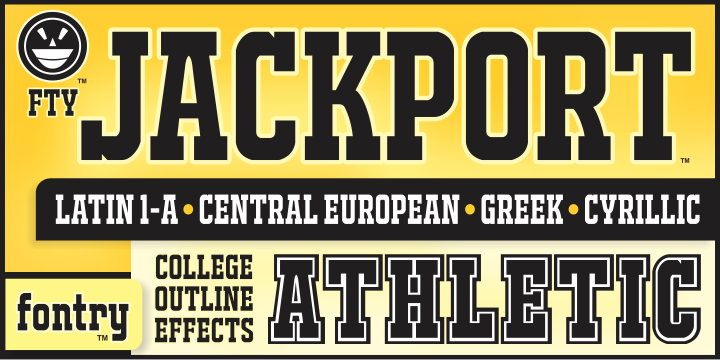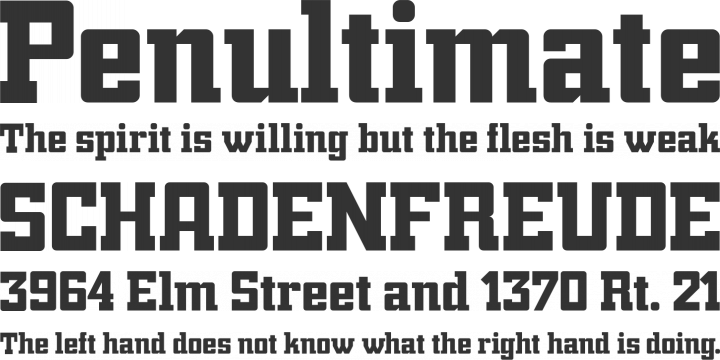
Suche schmale aber hohe Schrift ähnlich College
suche eine hohe Schriftart, die aber auch schmal sein soll.
Außerdem soll sie der College ähneln bzw. zum Thema Abschluss passen.
Wäre auch sehr gut wenn diese Umlaute hat.
Dieser College hier? Die ist ja für die Richtung schon relativ schmal, eine weitere Auswahl wäre hier, z.B. die Octin-Varianten (nur Majuskeln, Umlaute vorhanden, aber kein großes sz).
mir fallen da zwei relativ schmal laufende Schriften ein. Beide laufen schmaler als die Octin Sports.
Jackport NCV, nur Großbuchstaben, frei für nichtkommerzielle Nutzung,
Porn Star Academy *rotwerd* nur Großbuchstaben, keine Unlaute und scharfes s, frei für nichtkommerzielle Nutzung,
Hier noch zwei echt freie Schriften mit Umlauten und scharfen s von Abdulmakesfonts auf Dafont:
Pop Warner
Staubach
Das Schriftenhörnchen hat noch was unter Square ... läuft aber nicht sehr schmal ...
Trump Town Pro von CheapProFonts